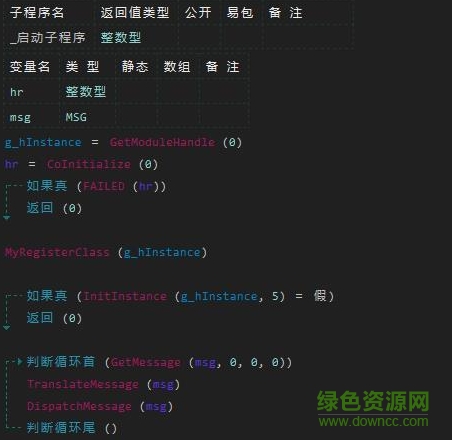
yahei consolas hybrid是一款程序員專用編程字體,也叫做consolas雅黑混合版字體,支持英文和中文,喜歡的可以下載試一試。
Yahei Consolas Hybrid 是一種合成字體,是由微軟雅黑的中文字體和 Consolas 的英文字體合成的,Consolas 字體是微軟專為程序員開發(fā)的一種字體,但沒有中文支持,所以 Yahei Consolas Hybrid 這種字體特別適合中英文的編程開發(fā),代碼編寫。在VS2008、eclipse和 EditPlus上來看代碼那個(gè)是舒服?。?qiáng)烈推薦所有與代碼有溝通的朋友使用此字體!